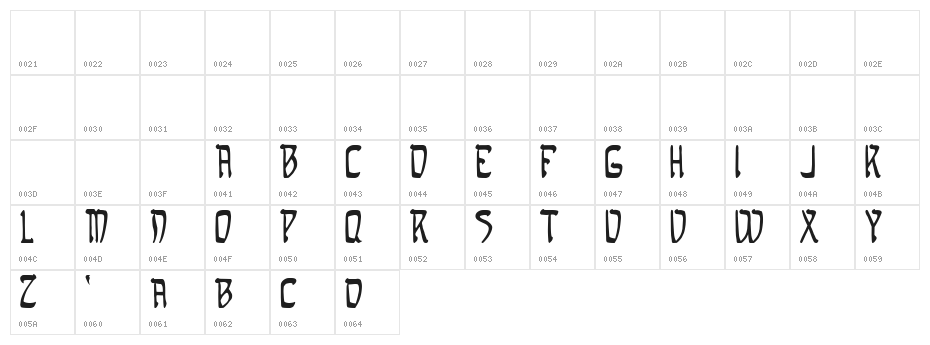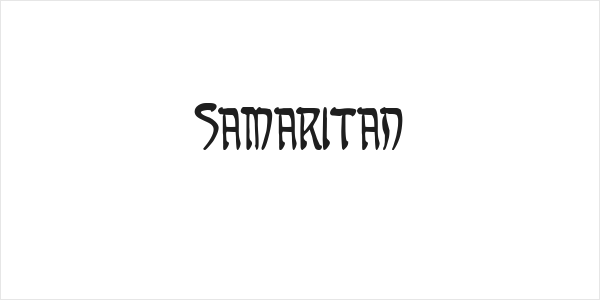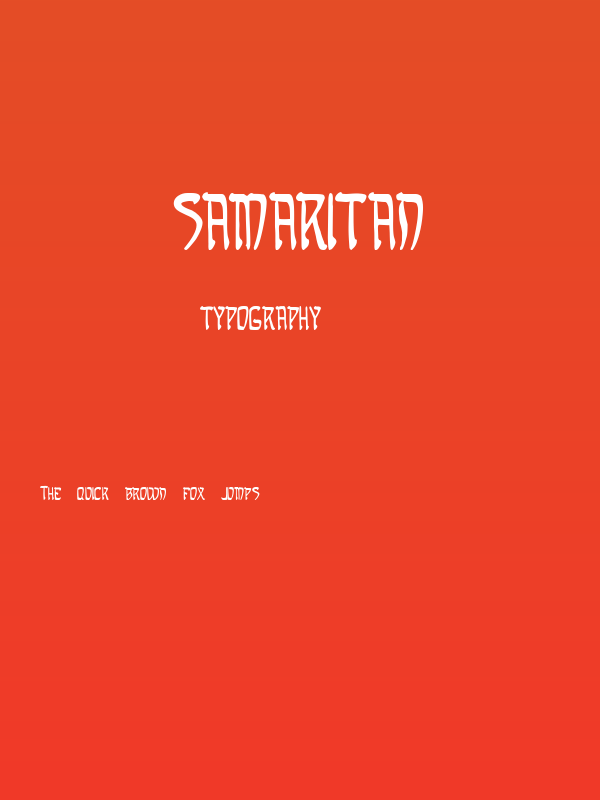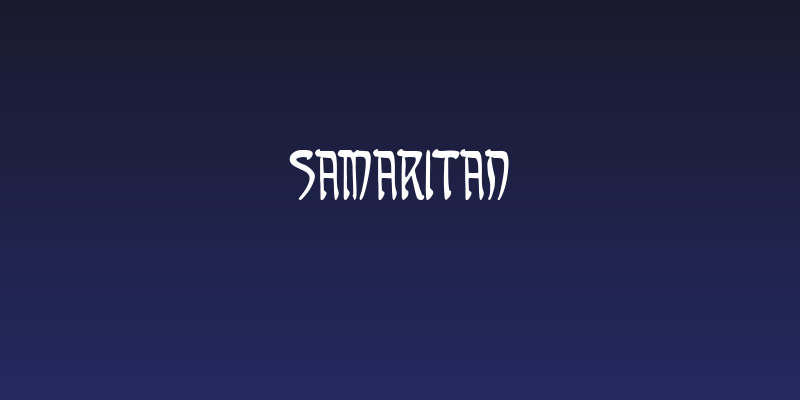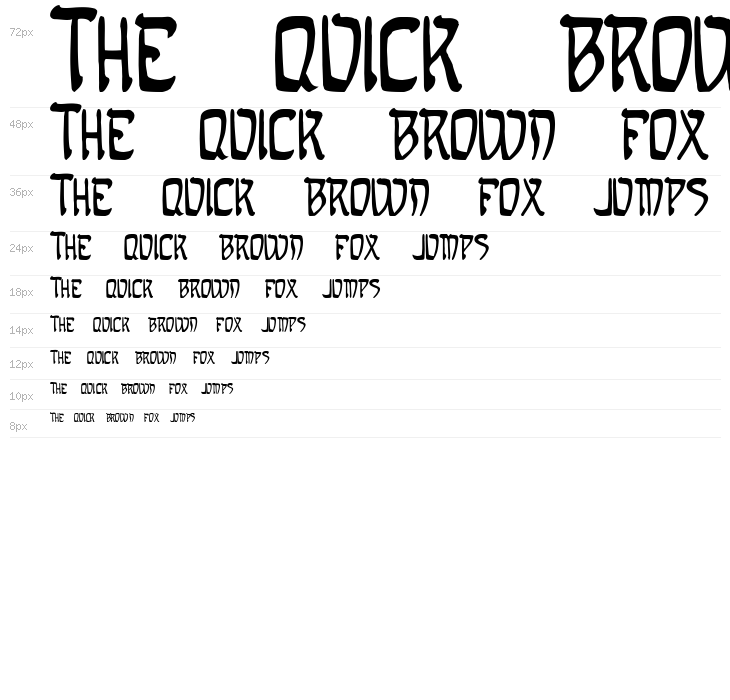
Samaritan Font
| Stile generale | Modern, Artistic |
| Progetti proposti | Ideal for creative projects such as posters, logos, and branding materials that require a distinctive and artistic touch. |